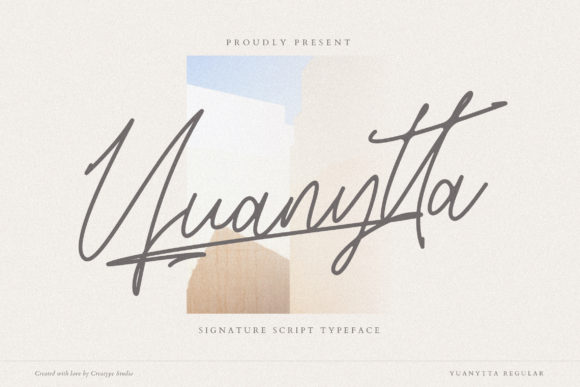
[Creativefabrica] Yuanytta Font (2021)
Название: Yuanytta Font (2021)
Yuanytta Script - это прекрасный и нежный шрифт, который излучает элегантность и класс.
Этот шрифт был создан специально для тех, кому нужен красивый и освежающий вид их дизайна.